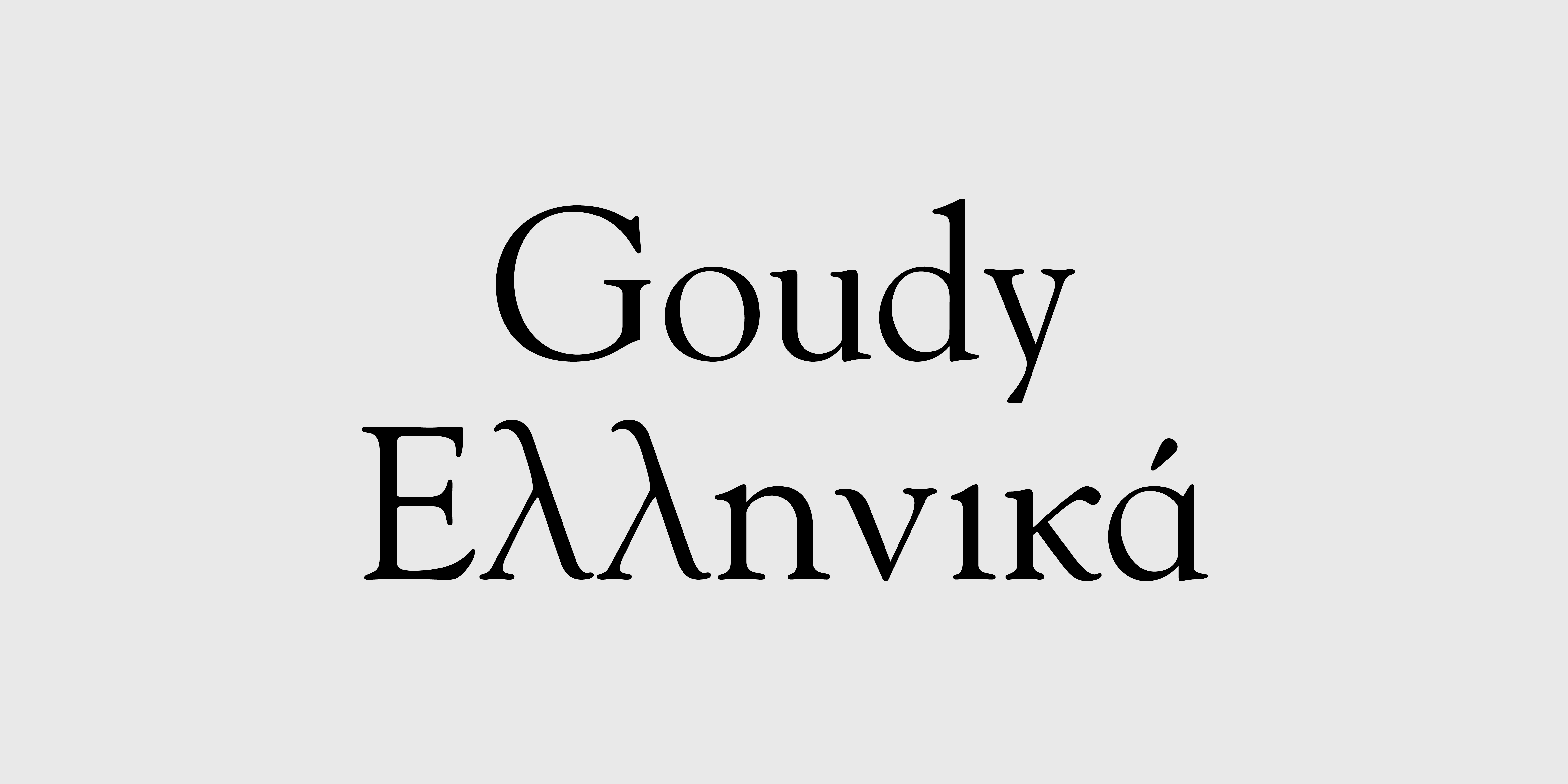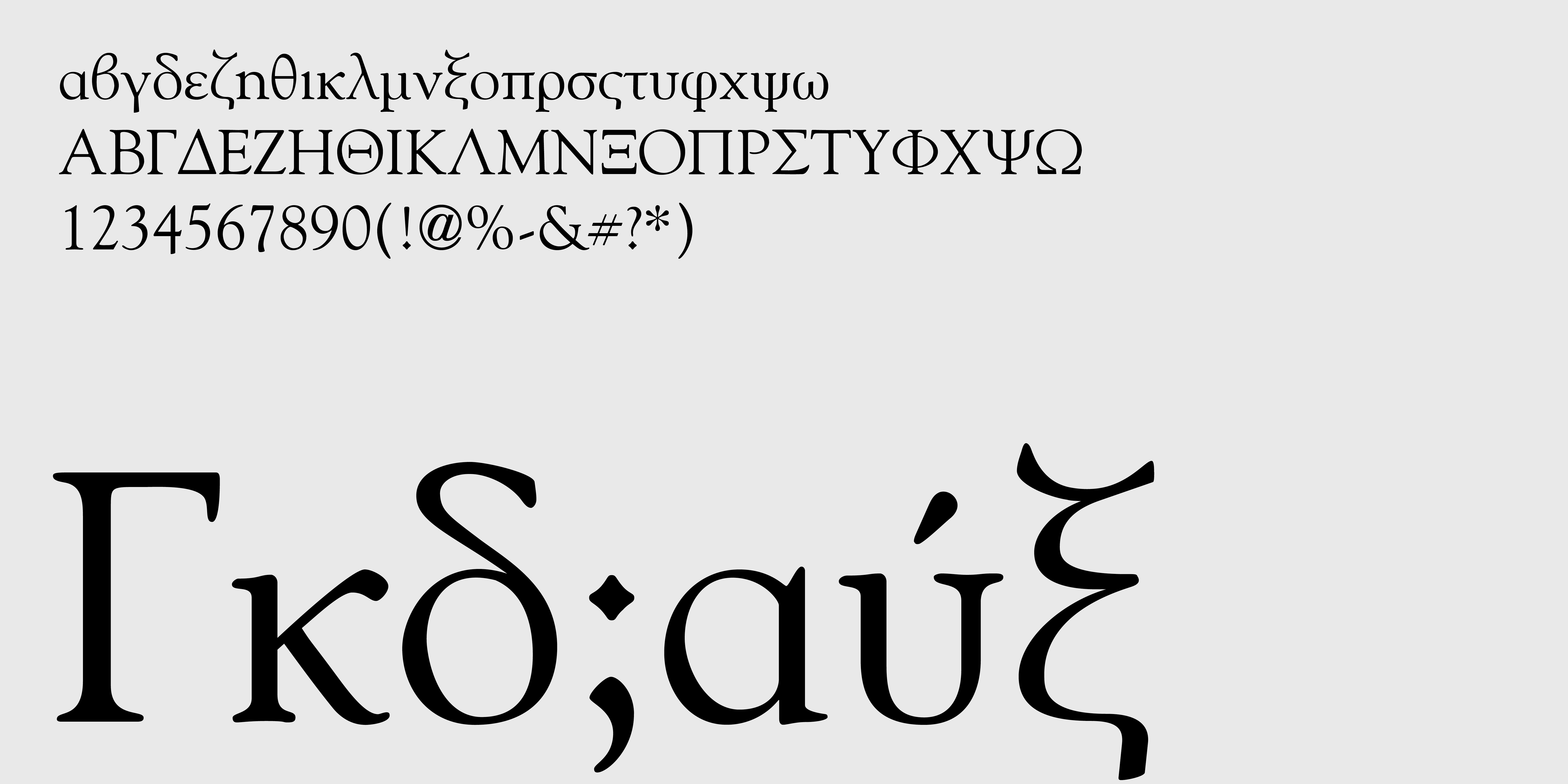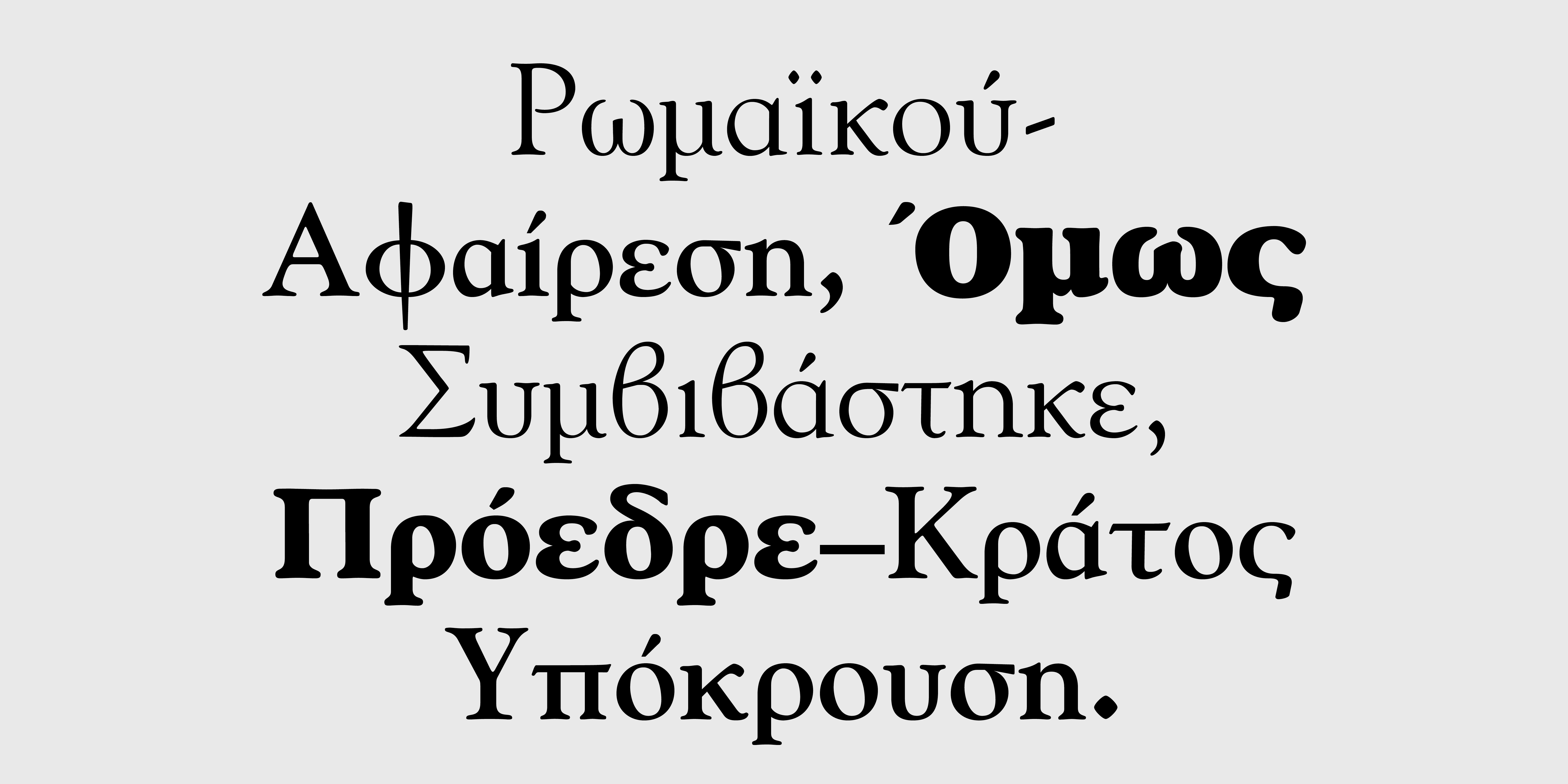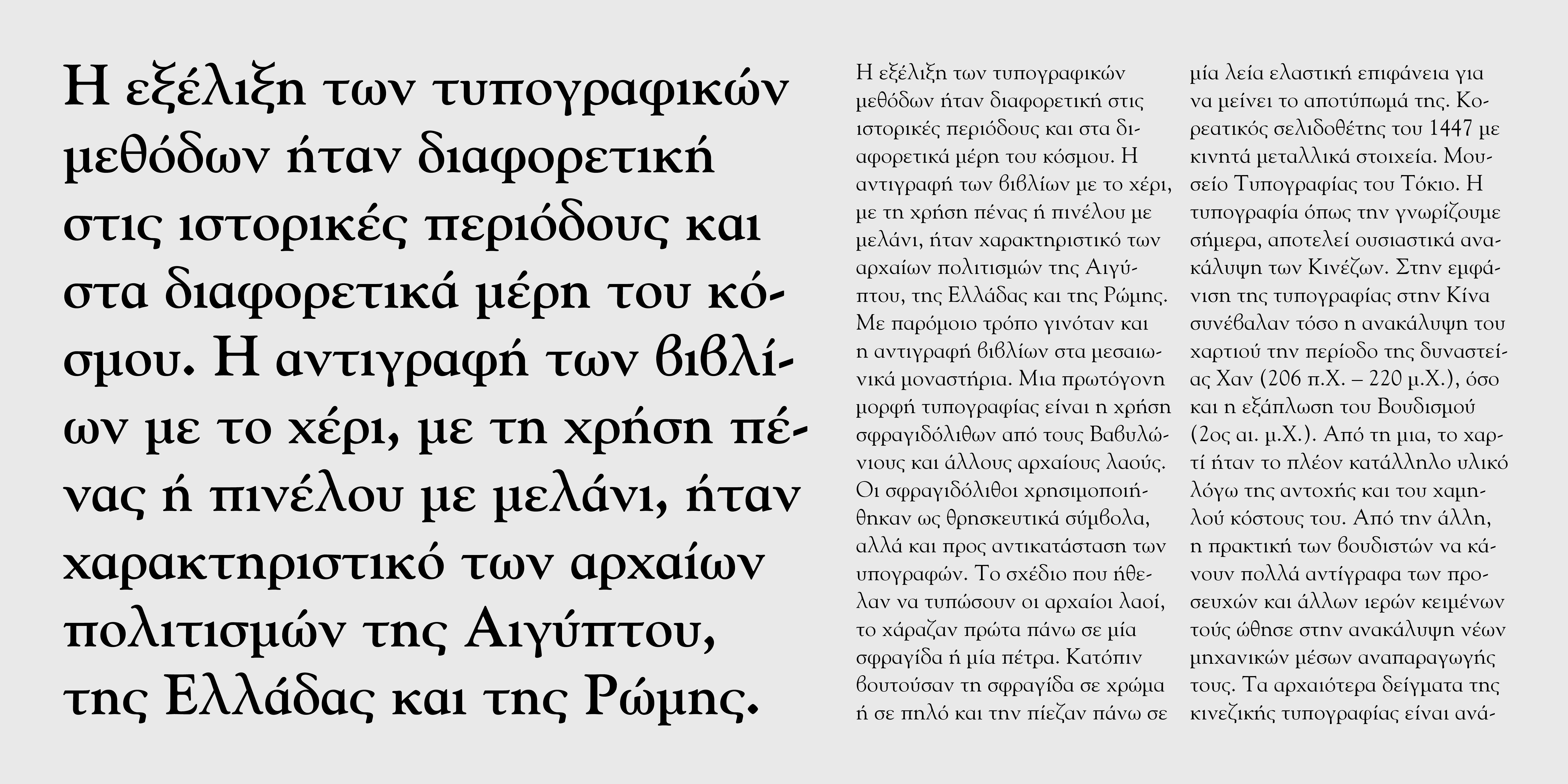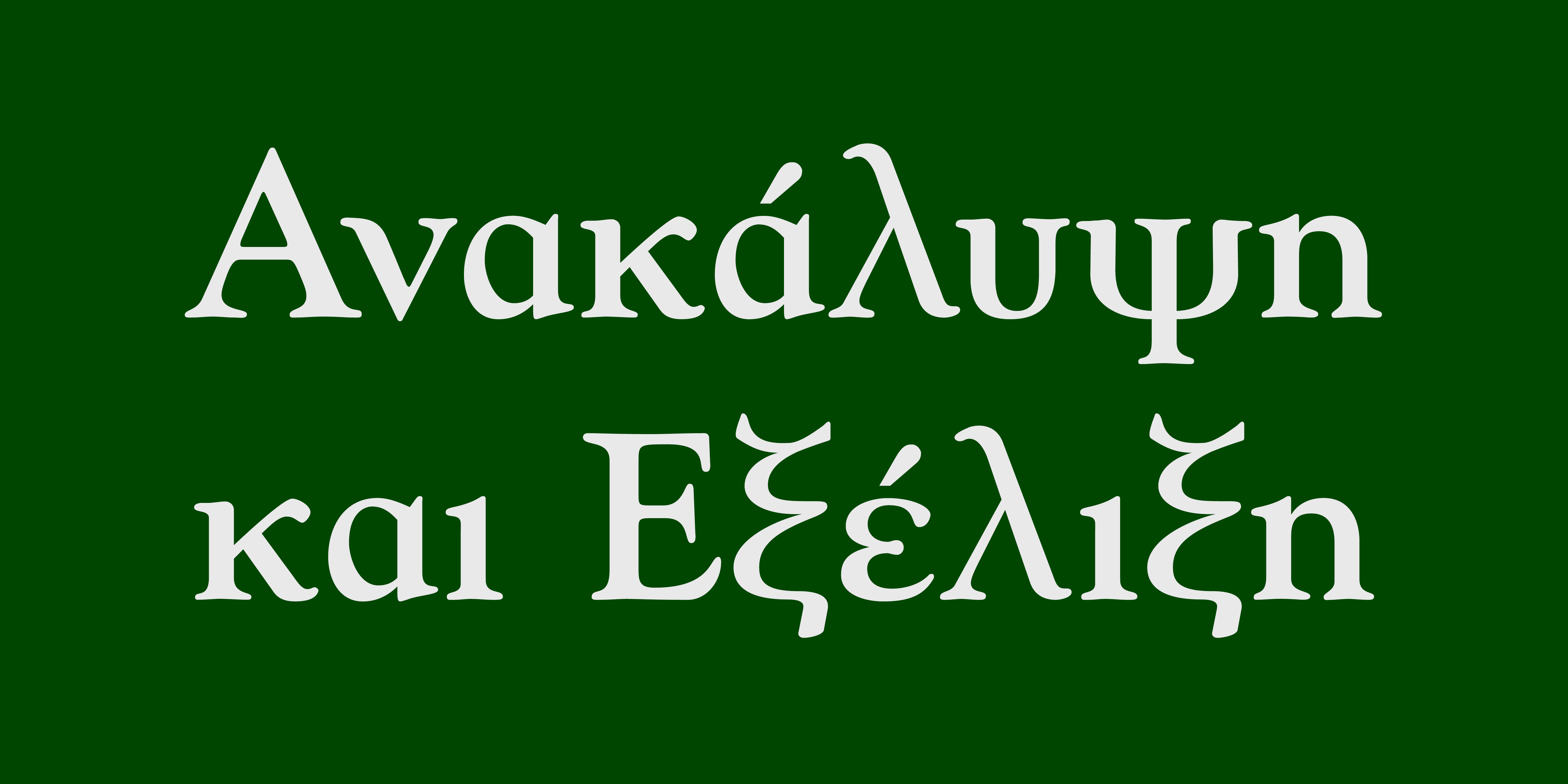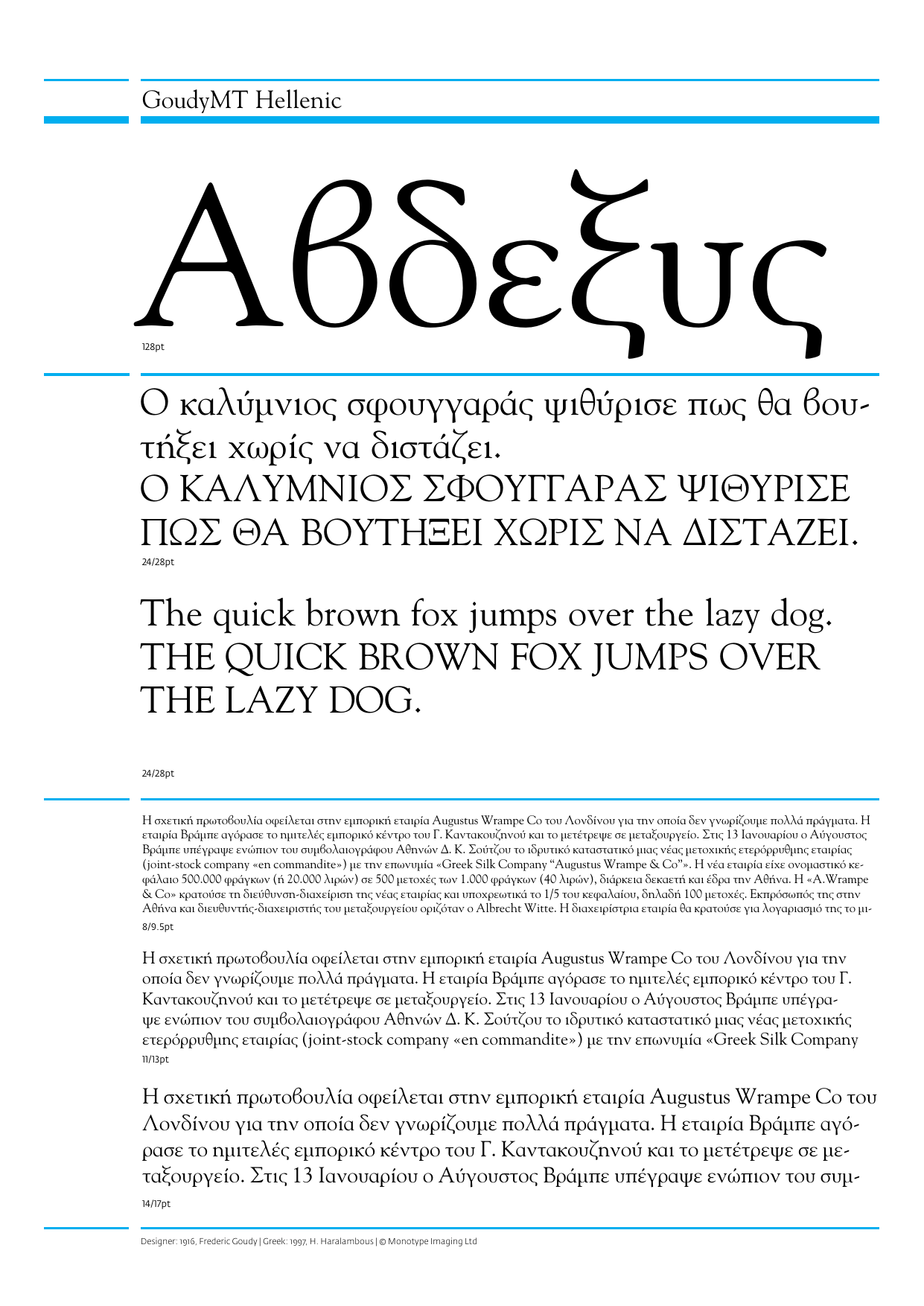
Goudy MT Ελληνικά
Εμπνευσμένη από τα κεφαλαία Froben που πιστεύεται πως είχαν σχεδιαστεί από τον Peter Schoeffer το νεότερο, γιο μαθητευόμενου βοηθού του Γουτεμβέργιου